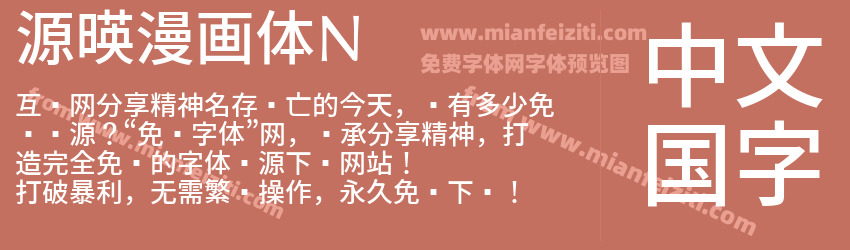
源暎漫画体是以日本版的思源黑体Semibold为基础,参考Light字重制作了平假名和片假名。因为骨骼来源于黑体字,所以在漫画台词中混合使用思源黑体、源真黑体等字体也可以毫无违和感地使用。这款字体削减了横笔的粗细,使字体看上去更具现代感。特别适合用于海报标题,LOGO等方面的设计。因为这个字体以面向漫画为主要用途,所以主要是与反映出的黑体汉字组合而成的“源暎漫画体”。
由于此款字体是通过电脑程序自己处理而成的字体,所以有可能会某些字存在变形的问题,所以大家在使用之前注意检查哦。